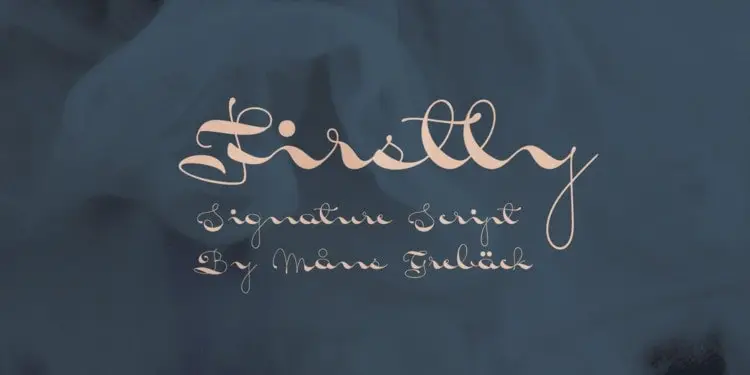
Firstly Script Font – Download Grátis
A Firstly Script Font é uma elegante tipografia script moderna que transmite autenticidade. Criada por Måns Grebäck entre 2019 e 2020, essa fonte manuscrita foi projetada para combinar com uma ampla gama de aplicações desde marcas sofisticadas até mensagens memoráveis no Instagram. Suas linhas onduladas e seu fluxo suave dão um toque atraente que equilibra os projetos ou logotipos em qualquer formato, garantindo uma personalidade harmoniosa. Com suporte lingüístico extenso, abrangendo todos os scripts latinos europeus, esta fonte inclui tudo o que você precisará: desde letras maiúsculas e minúsculas até aspas e números. Perfeita para designers profissionais e criadores de conteúdo nas redes sociais, essa Firstly Script Font é uma escolha inteligente para qualquer projeto que deseje transmitir elegância e sutileza através do texto.